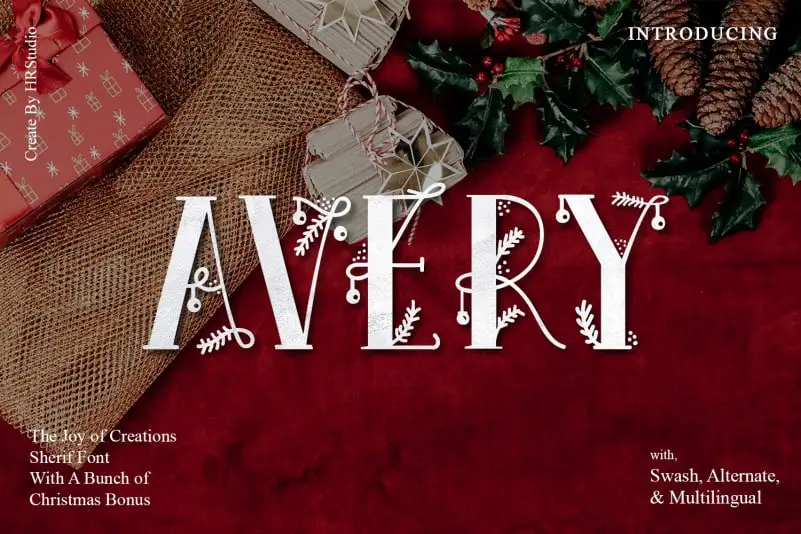
Avery Display Font – Download Grátis
A Avery Display Font é uma nova criação do studio HRStudio, cujo nome remete a uma fada que sempre nos proporciona bênçãos e felicidade por meio das nossas ações diárias. Inspirada na amizade sincera que eu sentia pelo meu gato perdido recentemente, essa fonte foi desenvolvida como uma homenagem especial ao nosso companheiro de quatro patas. Sua elegância gráfica e sua capacidade única em transformar texto em arte tornam-a um recurso indispensável para designers dedicados a criar mensagens impactantes e decorativas. Esta font é perfeita tanto para design gráfico quanto para publicidade, ilustrações ou qualquer projeto que busque expressar uma paixão inigualável pelo amor dos gatos. Com o Avery Display Font, você pode transformar suas ideias em obras de arte enquanto honra a memória do seu querido amigo peludinho.
Designer: HydricDesign